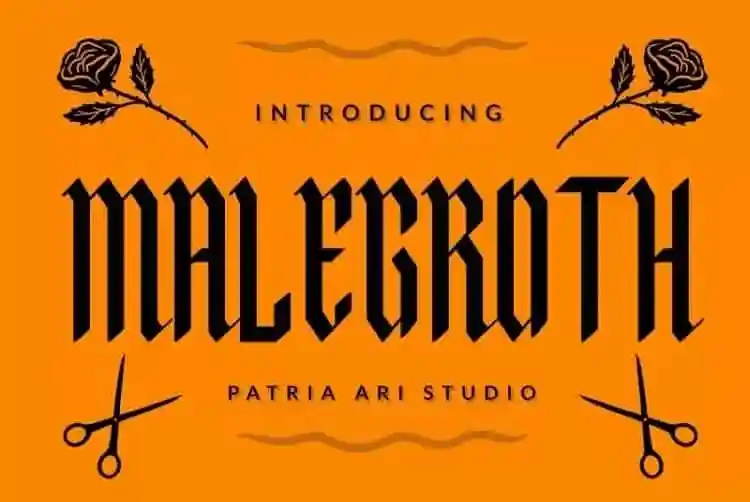
A Malegroth Blackletter Font é uma tipografia para uso no display que se destaca por seus contornos simples e elegantes, perfeita para criar ambientes carregados de emoção sombria. Esta bela face gothic traz aos designers e criadores de conteúdo a oportunidade de explorar o espírito do gótico em projetos variados. Inclui setes completos de letras maiúsculas e minúsculas, números e símbolos, bem como alternativas adicionais para alguns caracteres de uso comum. A Malegroth Blackletter é ideal para uma ampla variedade de aplicativos criativos, incluindo logos e embalagens de marca, headlines e placas de sinalização, cartazes publicitários, tags e rótulos, textos impressos em materiais de propaganda ou em peças especiais. A Malegroth Blackletter é uma escolha perfeita para qualquer projeto que precise transmitir emoções intensas com destreza no formato gothic.